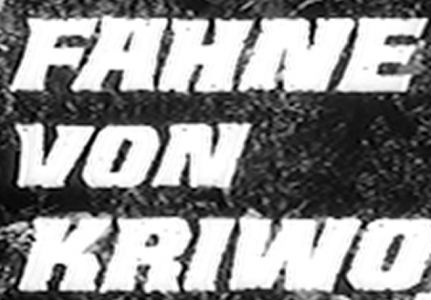
das ist wieder so eine hübsche Schrift, die wahrscheinlich nicht auf einem echten Schriftschnitt basiert. Welcher kommt dem Muster hier am nächsten? Die Serpentine ist mir noch ein bisschen weit entfernt ...
Danke, Robert, solche oder ähnliche »Techno-Schriften« habe ich mittlerweile gefunden. Ich war hängengeblieben bei der Crillee Extra Bold Italic – vor allem wegen der Serifen-artigen Spitzen. Was mir halt fehlt, ist dieses markante, irgenwie russische K ... Ansonsten würde ich die Crillee nehmen :D
etwas nachgearbeitet und bei myfonts hochgeladen wird noch
empholen. naja.
deine vorlage würde mich interessieren, ist das eine alte bleischrift?
oder vielleicht sogar per hand gezeichnet?
vorallem weil zwei unterschiedliche schriftgrößen verwendet wurden, für eine bleischrift scheint mir allerdings der unterschied zwischen den
schriftgrößen zu gering. oder sollen das kapitälchen sein?
wenn es ein bleifont ist kann ggf. 'bleisetzer' nachhelfen.
Vielen Dank für Deine Mühe :D ! Ich habe mir dann die Crillee gekauft, ist ok. Nee, das ist ein Bild von der MAZ eines DEFA-Filmes ...
Ich benötige die Schrift für ein Cover, und die Schrift muss der Original-Typo zumindest ähnlich sein :wink:
peinlich ist mir eher, dass ich nie (!) freiwillig eine 'Univers',
'Frutiger', 'Futura', 'Gill', 'Optima' oder 'Garamond' oder andere
klassiker einsetzten würde.
ich weiss nicht wieso, vielleicht kann ich sie einfach nicht mehr sehen.
sorry. es sind trotzdem großartige schriften.
ich verwende sehr oft die 'DIN', 'Fago' und 'Sauna' vielleicht ist dies oft
peinlich weil nicht unbedingt alle einsatzgebiete zu diesen schriften passen.
für mich sie jedoch zeitlose klassiker. mal sehen wie lange noch ;)
beispiel:
eine DIN passt sicher nicht gut zu einem sporthotel bzw. sportanlage,
trotzdem habe ich sie dort als hausschrift genommen. peinlich? vielleicht.
sieht trotzdem gut aus.
im headline bereich habe ich auch meine klassiker:
90 % der house industries fonts oder vergessene klassiker wie z. b. 'Tasse', 'AG Book' und 'Akzidenz Grotesk' sind da ganz oben mit dabei.
neu dazugekommen und wiederentdeckt ist die 'Clarendon', diese nutzt ein kunde von uns als hausschrift (nicht unsere idee), wir haben dies
dann ausgeweitet auf den condensed- und den bold-expanded-schnitt.
das passt gut und wirkt nicht ganz so altbacken und langweilig wie die
üblichen schnitte. die clarendon war uns natürlich nicht neu, jedoch
diese restlichen 3 schnitte ... die habe ich vor einigen jahren entdeckt.
früher habe ich in der lehre viel 'Swiss' verwendet, einfach weil sie
ihnen unter die arme ...
fazit.
es gibt fonts die ich von der bettkante stoßen würde, jedoch ziehe ich
sie für ein passendes schläferstündchen gerne wieder hoch und helfe
ihnen unter die arme ...
schön lebensnah formuliert!
Mich lässt derzeit die ITC American Typewriter "nicht mehr los".
@ peinliche Lieblingsschriften
Herb Lubalin hat einige ausgesprochen hässliche – peinliche – Schriften designt. Ich liebe sie dennoch alle.